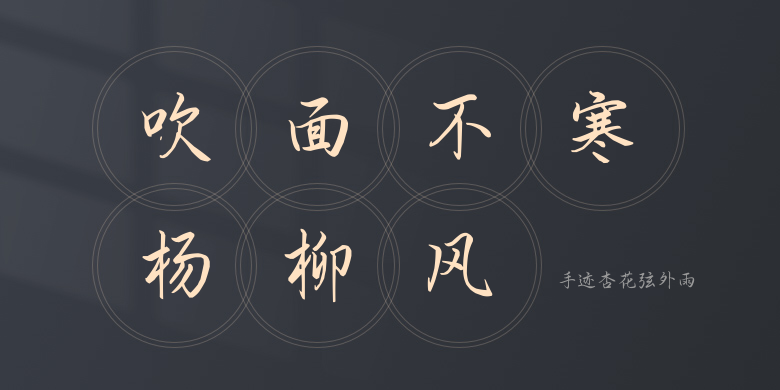
手迹杏花弦外雨
手迹杏花弦外雨,这款字体结构工整、笔画清晰,兼顾美观与易读性,适用于标题、正文、海报、包装、LOGO 等多种场景。字形优雅稳定,风格百搭耐看,适配日常排版与创意设计,让文字呈现更舒适、更具质感。手迹杏花弦外雨一笔一画,皆是细节,以均衡的比例、流畅的线条打造舒适视觉体验,字形端正大气,风格简约现代。无论是商业设计、品牌宣传还是日常排版,都能轻松驾驭,让文字更有格调与力量。手迹杏花弦外雨字体下载。